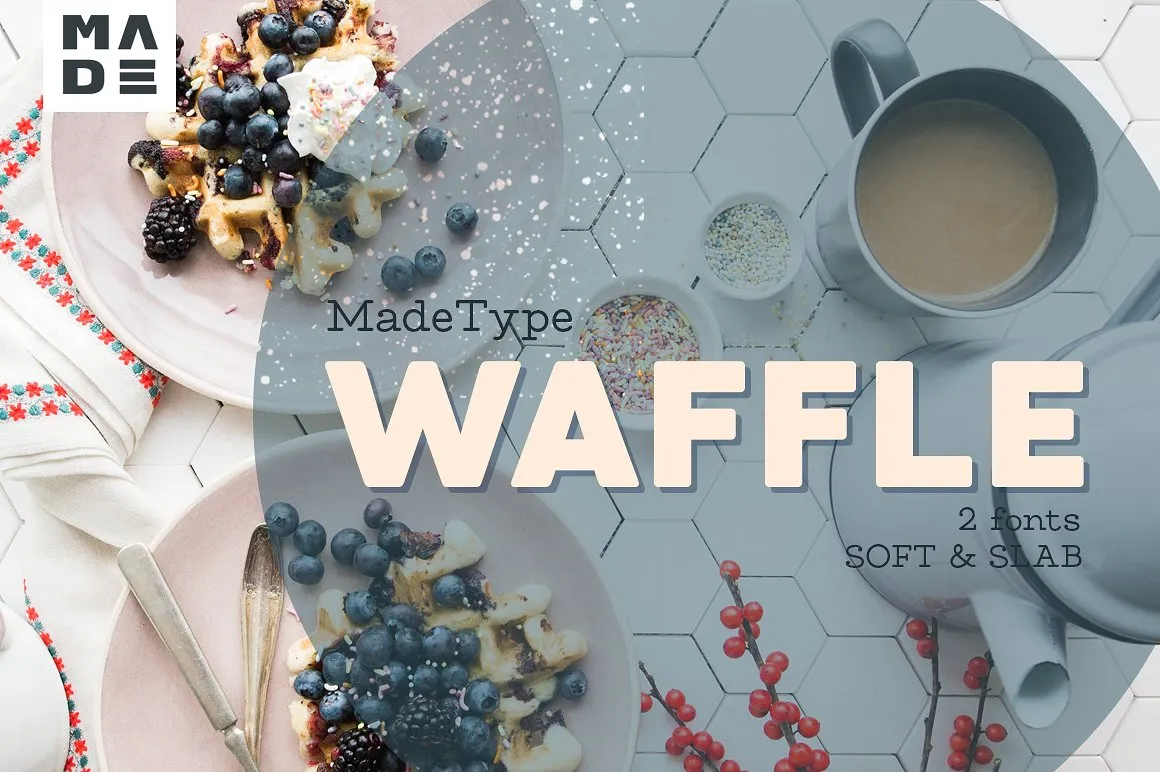
A MADE Waffle Font é uma escolha perfeita para quem procura uma fonte sans-serif que se destaca em ambientes de logotipos e cabeçalhos. Inspirada na essência fresca e divertida dos waffles, essa família de fonts foi criada para a combinação única de sua ideia. Com aplicação ampla nos designs de restaurantes e cafés, é uma font ideal que adicionará um toque especial à identidade visual desses estabelecimentos. Para designers inovadores que buscam uma maneira fresca de dar vida aos seus projetos, a MADE Waffle oferece duas opções de fontes que permitem criar combinações singulares e impactantes. Suas linhas leves e curvas suaves garantem um resultado gráfico dinâmico e moderno, se encaixando perfeitamente em qualquer design moderno que você possa criar. Através da combinatória de ideias de quem usa a MADE Waffle Font, o resultado é uma fonte elegante e versátil que não só adicionará um toque único ao seu trabalho, mas também ajudará a destacar sua marca ou projeto. Ideal tanto para uso em logotipos quanto para cabeçalhos e subtítulos, esta família de fonts será um complemento indispensável no seu arsenal de recursos gráficos.